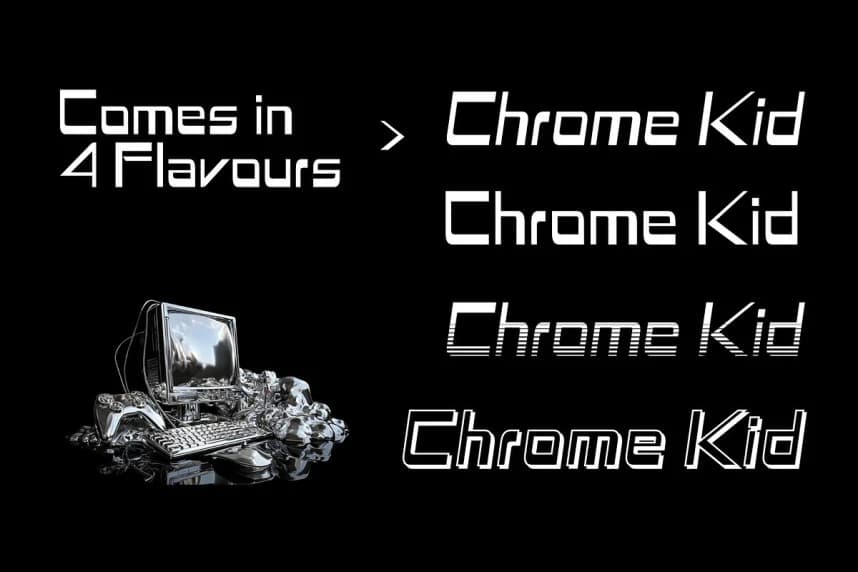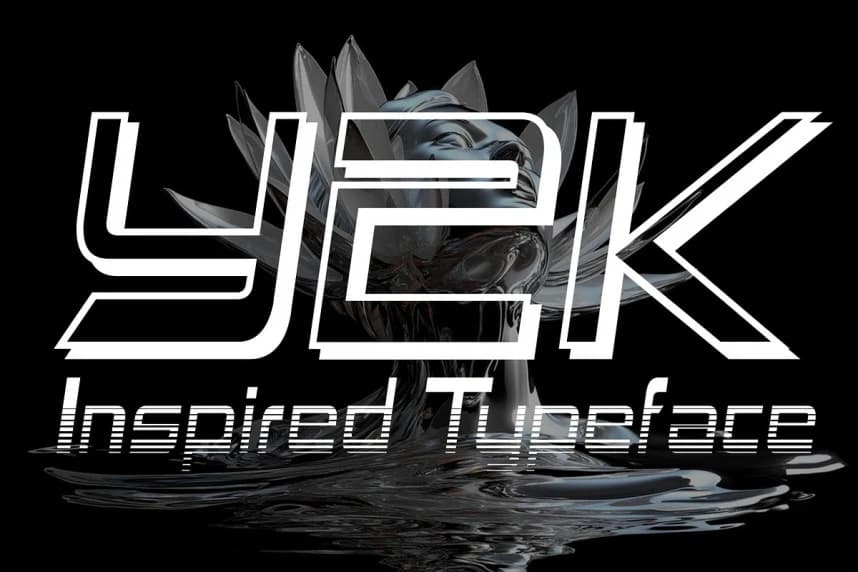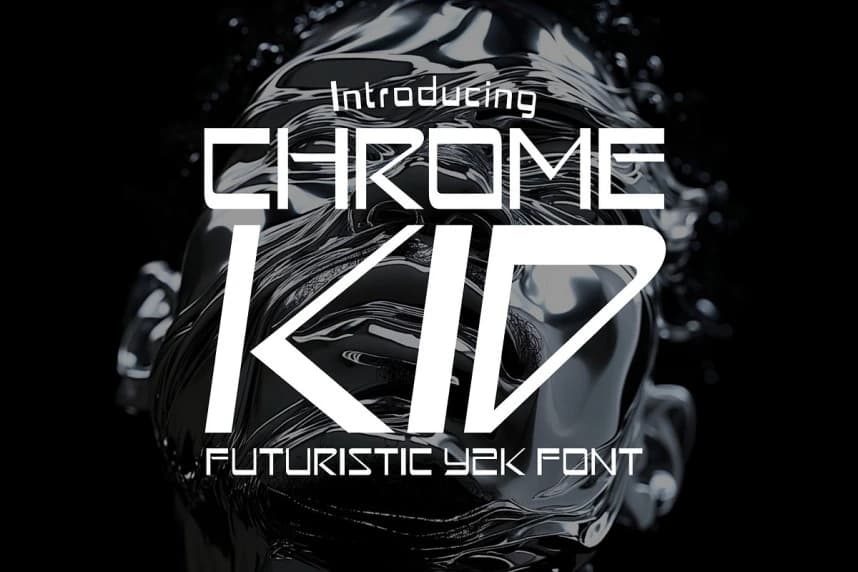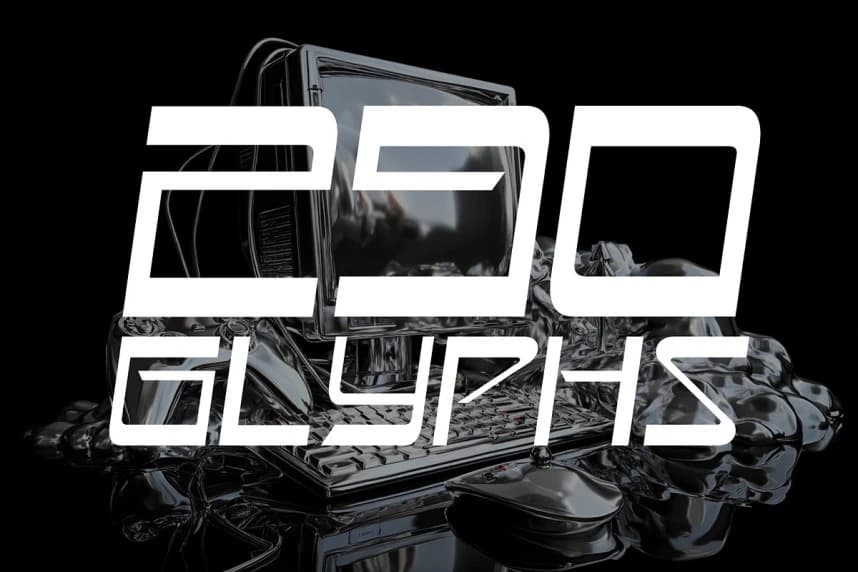
Chrome Kid Font, Y2K döneminin dijital rüyalarından ve techno estetiğinden ilham alan cesur ve çok yönlü bir fütüristik yazı tipidir.
Şık eğrilerle, metalik hissiyatlar ve siber isyan dokunuşuyla ChromeKid, dikkat çekmesi gereken tasarımlar için tasarlandı.
Chrome Kid Font, Y2K dönemi dijital düşler ve techno estetiğinden esinlenen cesur ve çok yönlü bir fütüristik yazı tipidir. Şık eğriler, metalik bir hava ve siber isyan dokunuşuyla ChromeKid, dikkat çekmesi gereken tasarımlar için tasarlandı.